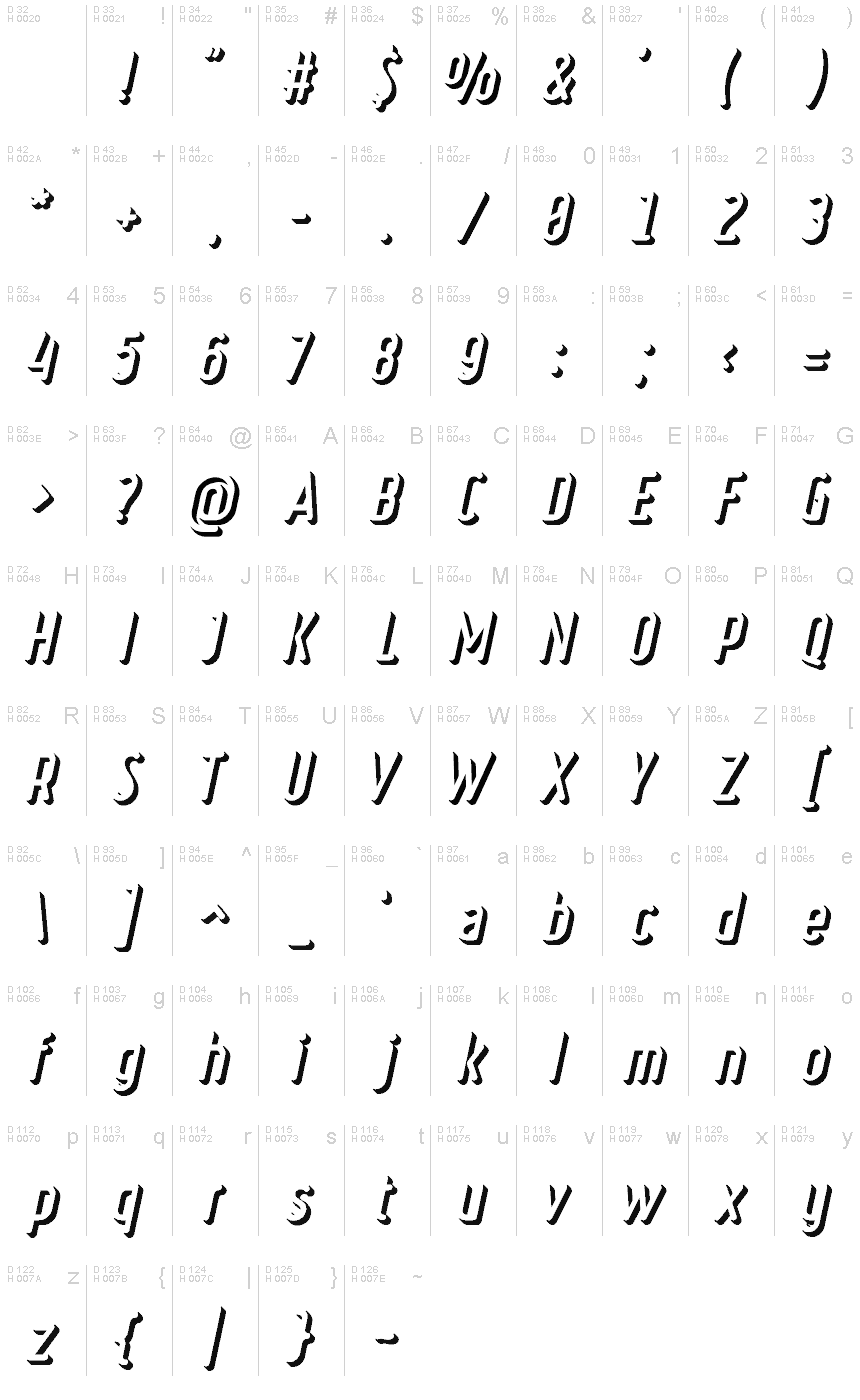
Ruler Volume Extrude Bold Italic
Ruler Volume è un set esteso di stili tipografici dove l'unico limite è la tua immaginazione. Puoi variare contorni e larghezze spostando i livelli, lasciando spazio aperto a nuove scoperte creative. Sebbene le combinazioni di pesi e stili possano superare le trenta varianti, il mio obiettivo è mantenere le cose semplici e intuitive.